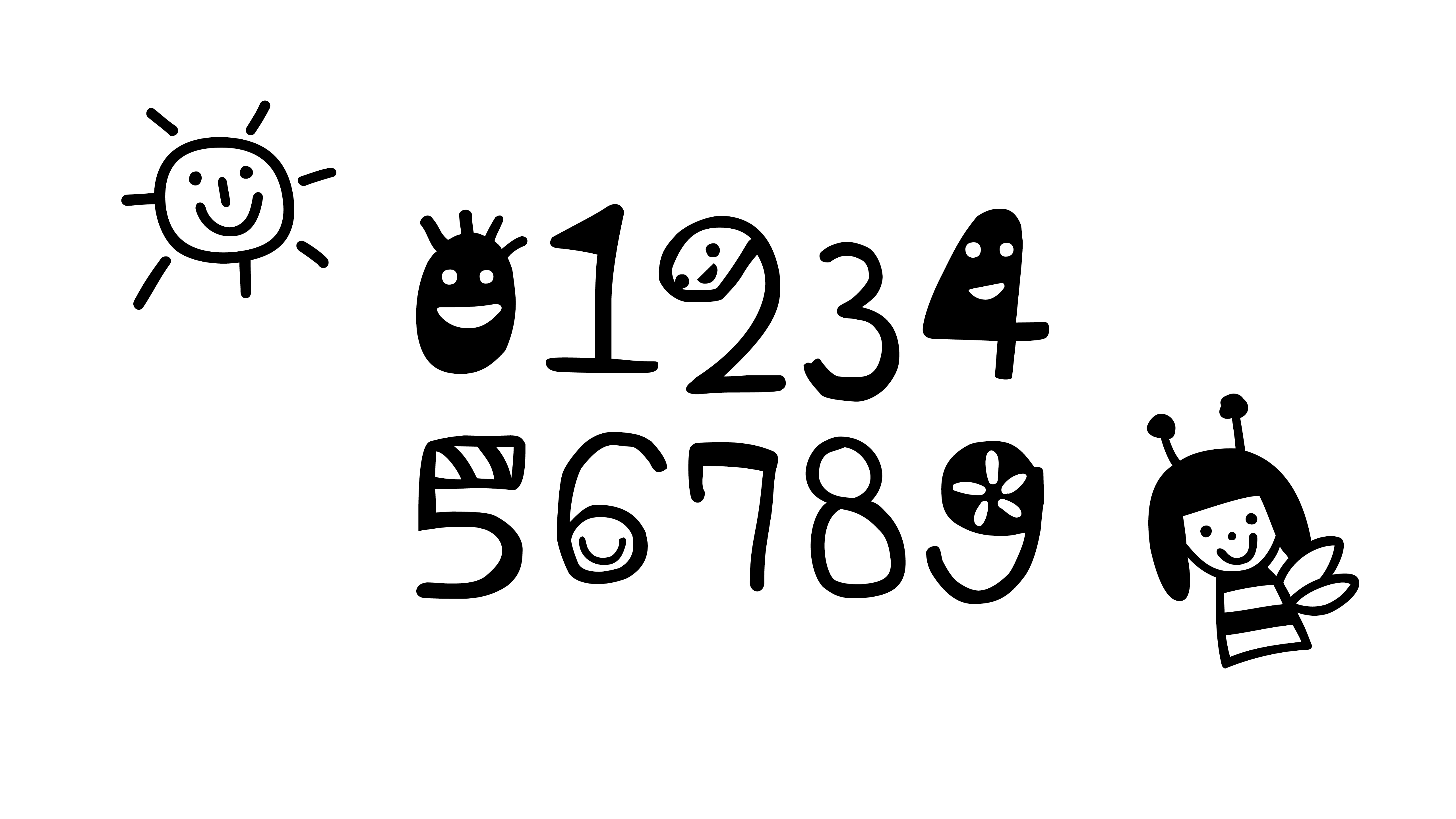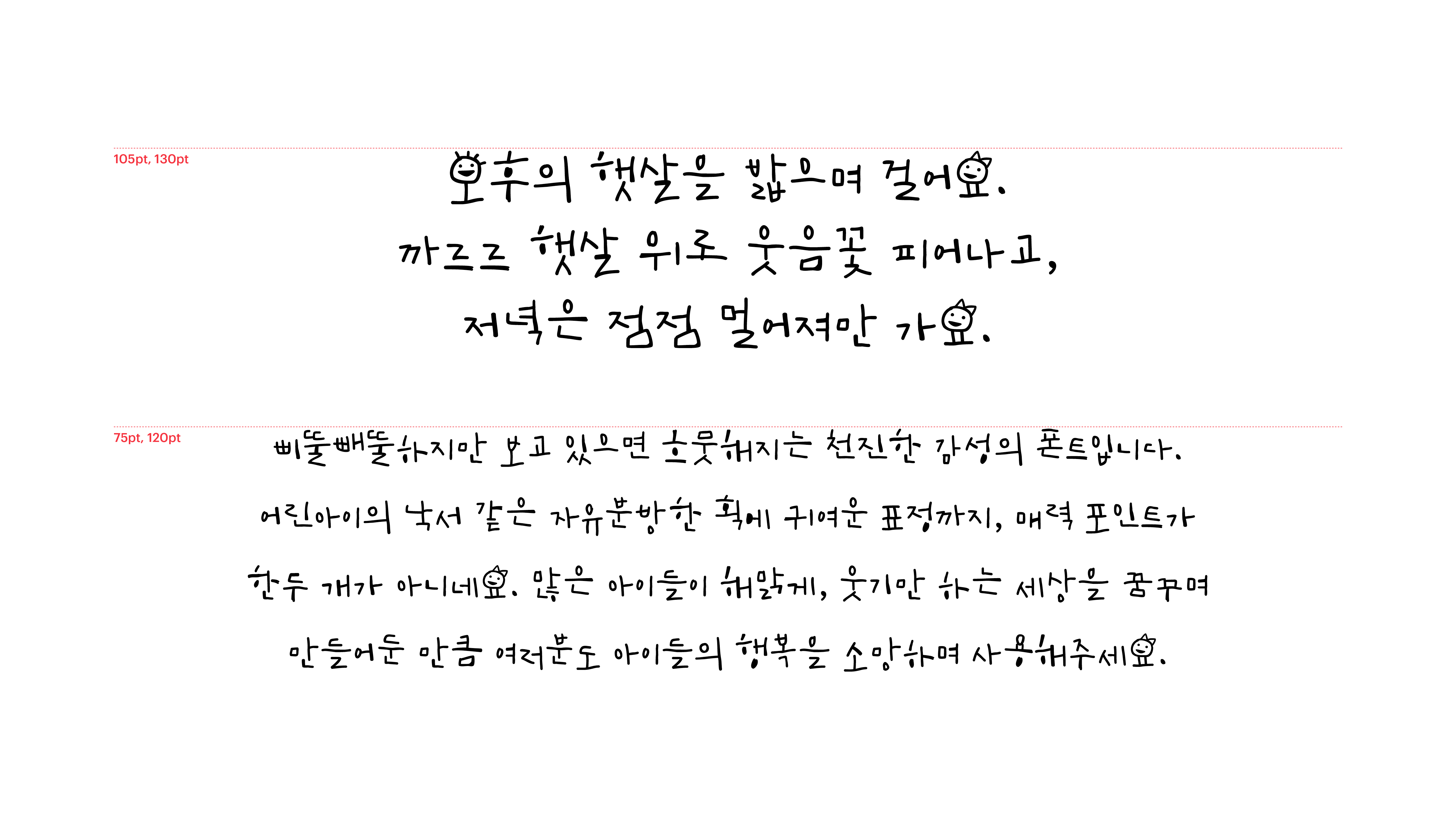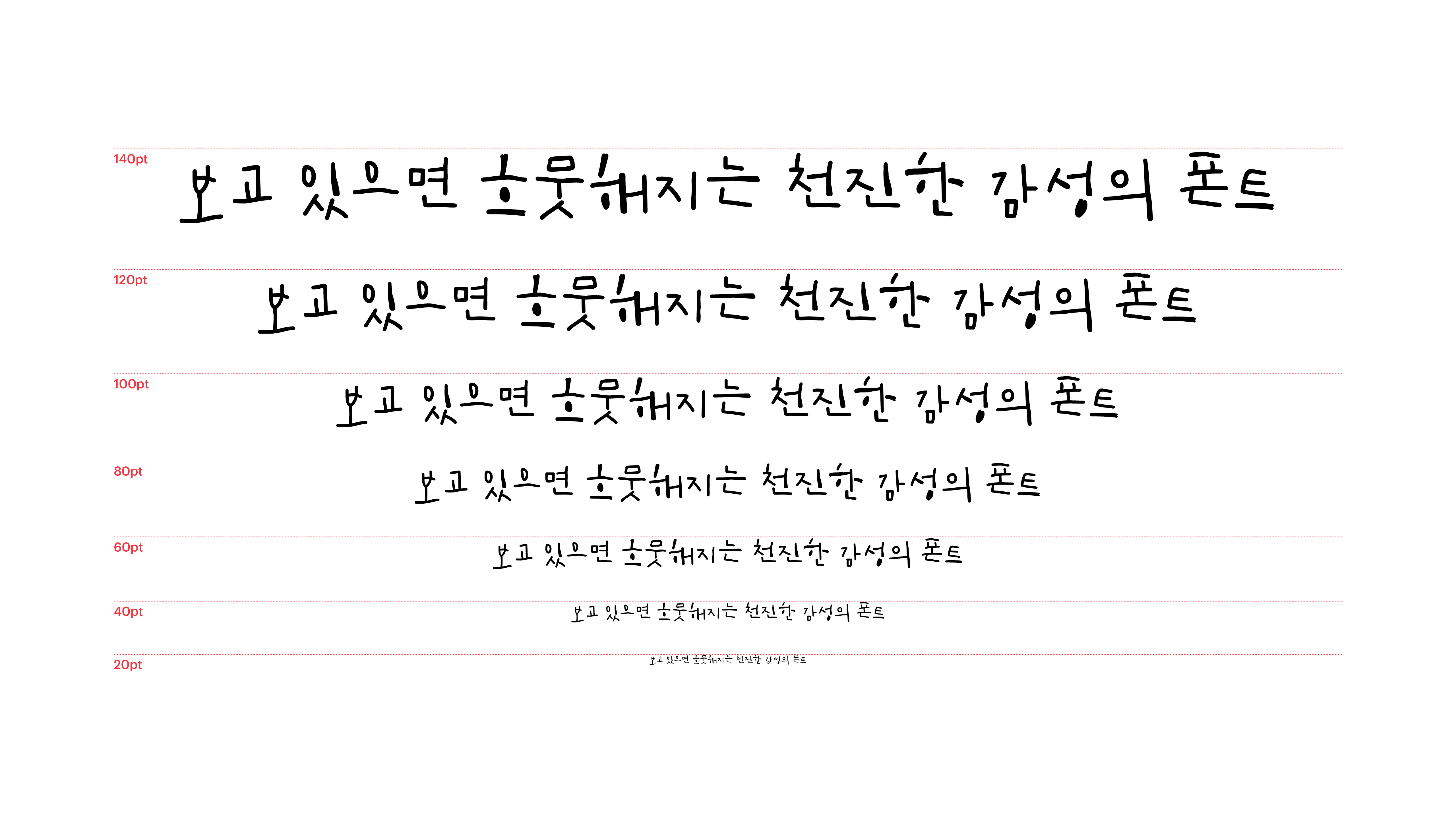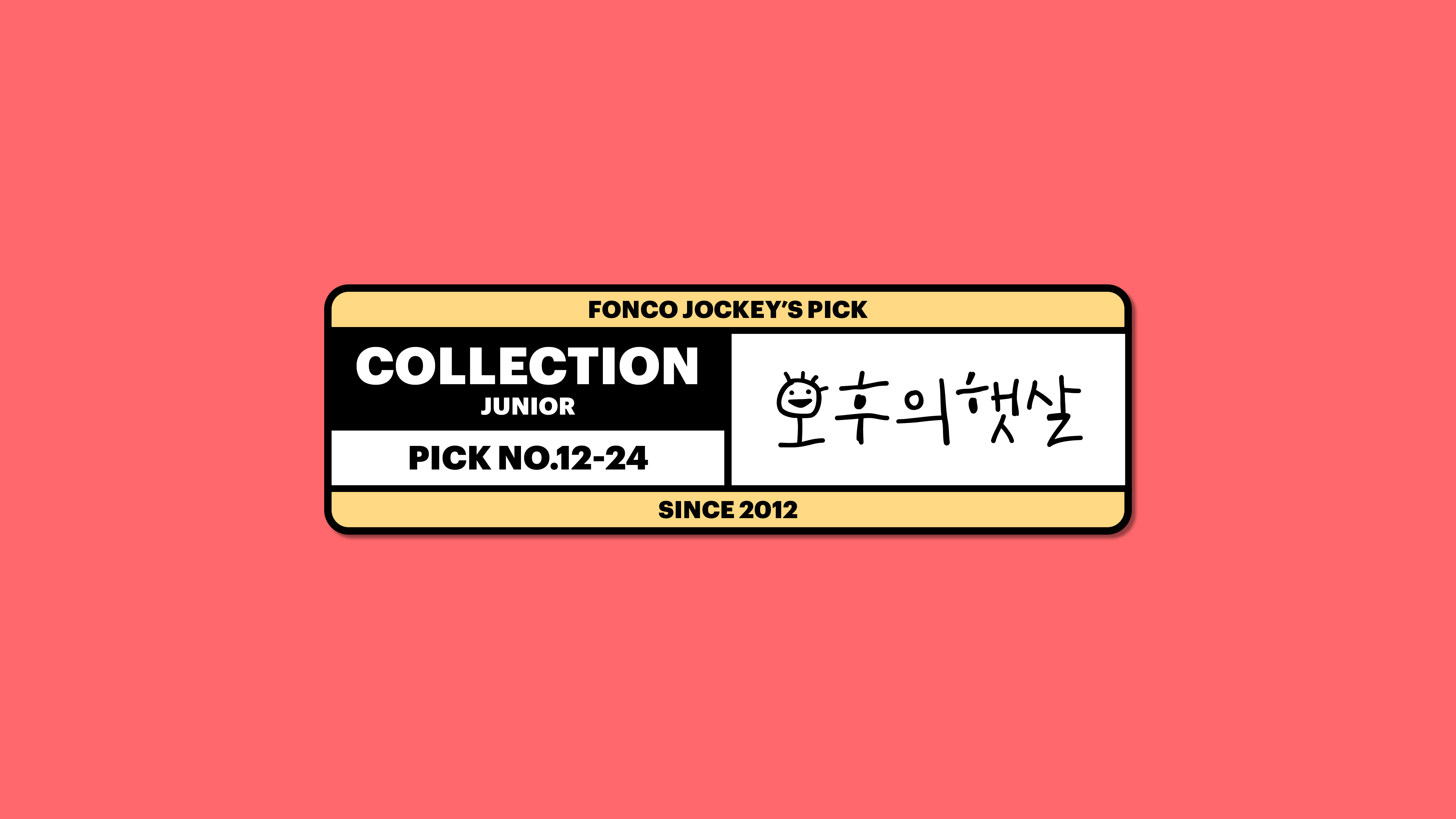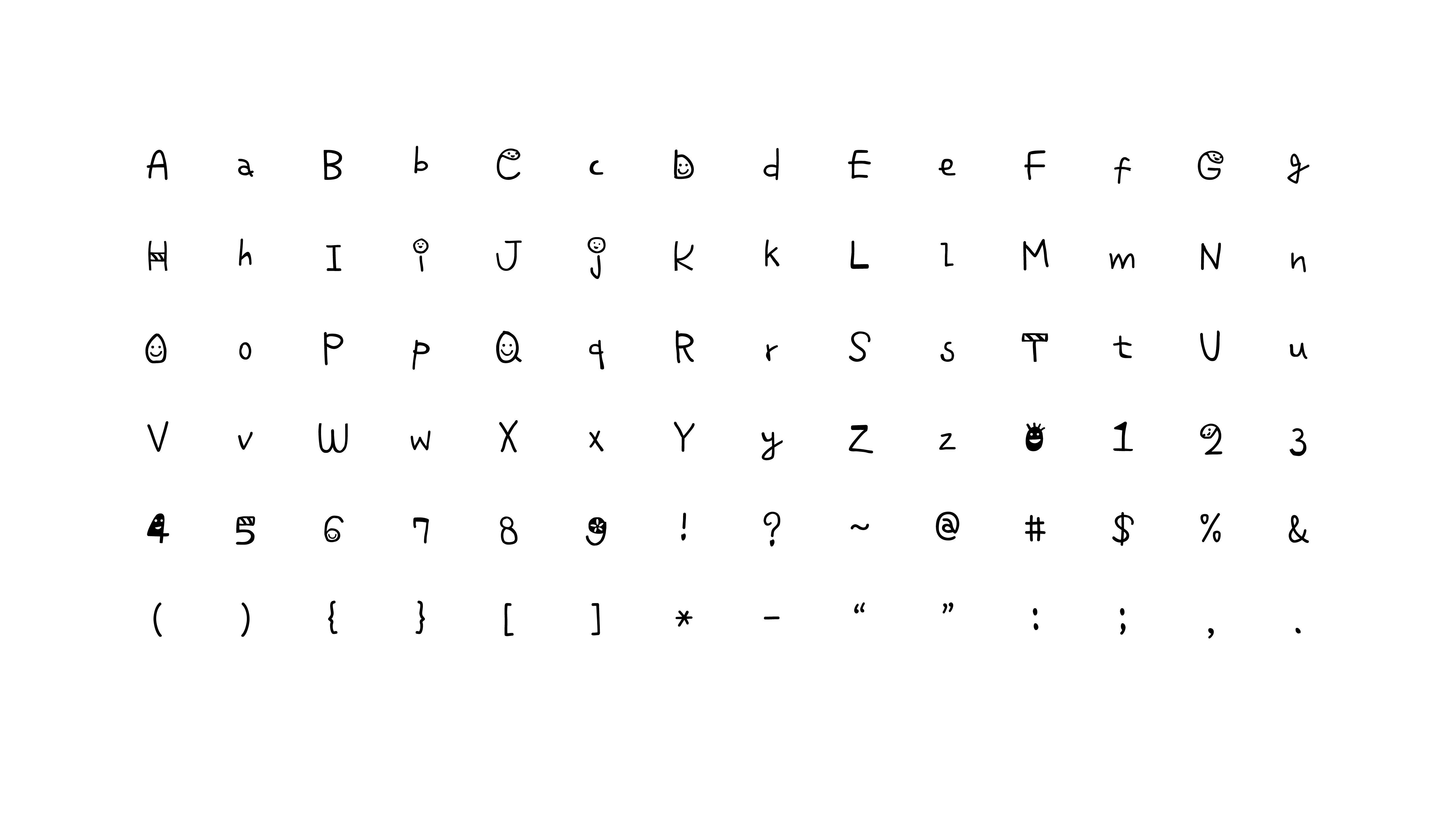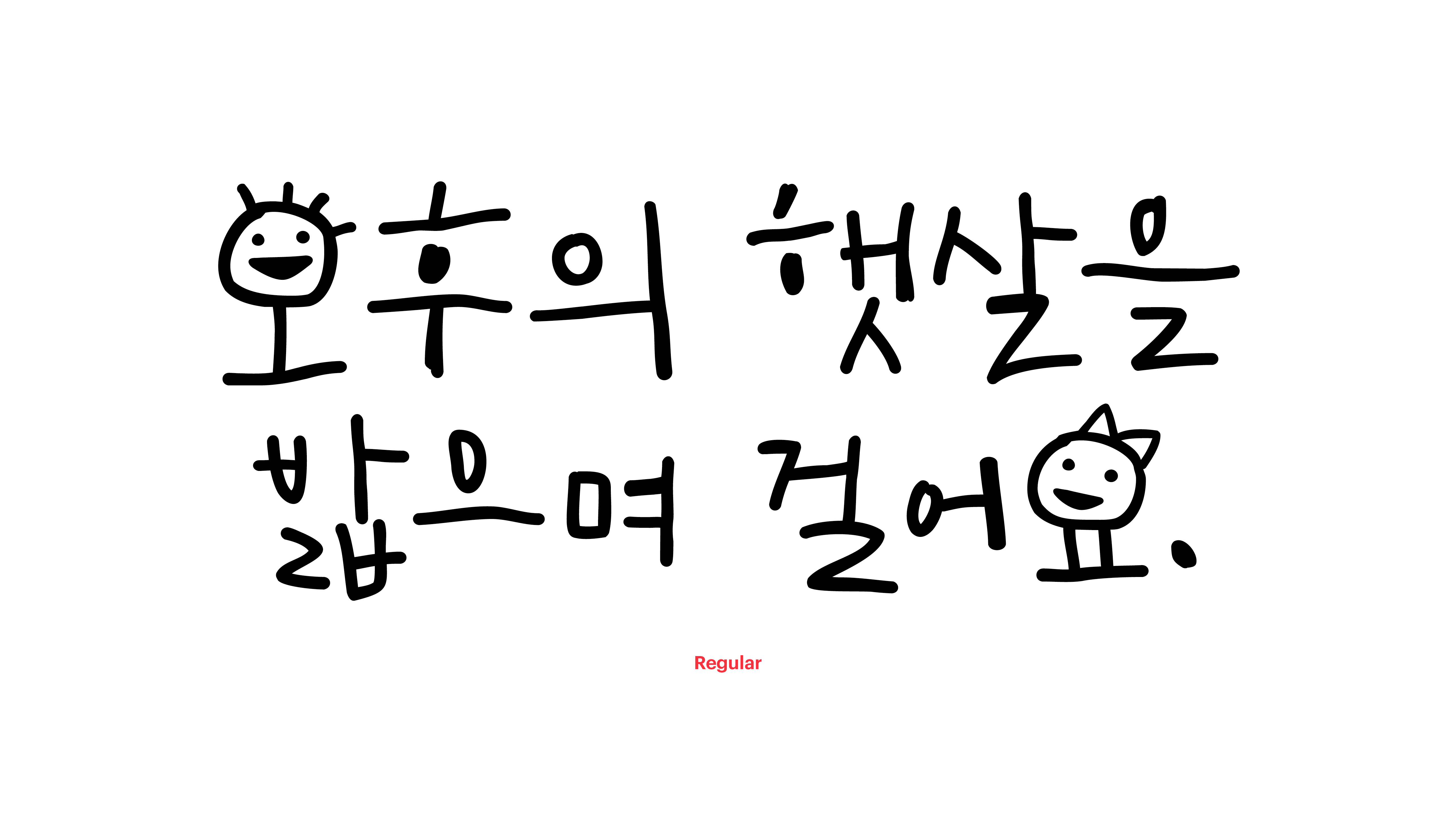
오후의햇살
Yoon 오후의햇살
삐뚤빼뚤하지만 보고 있으면 흐뭇해지는 천진한 감성의 폰트입니다. 어린아이의 낙서 같은 자유분방한 획에 귀여운 표정까지, 매력 포인트가 한두 개가 아니네요. 많은 아이들이 해맑게, 웃기만 하는 세상을 꿈꾸며 만들어둔 만큼 여러분도 아이들의 행복을 소망하며 사용해주세요.